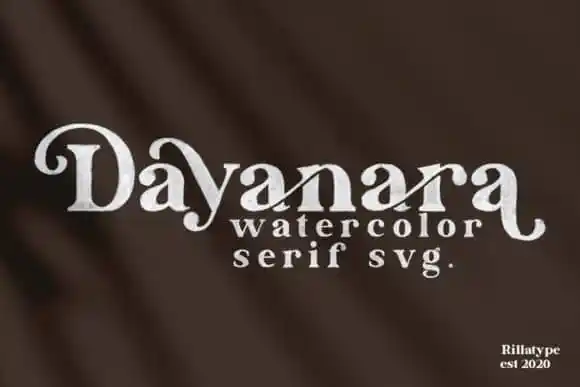
Dayanara Serif Font – Fonte Grátis
Dayanara Serif Font – Download Grátis
Dayanara Serif Font
A ‘Dayanara Serif Font’ é uma elegante tipografia serifada com estilos vintage moderno, que incorpora sutis ligaturas perfeitas para dar vida a textos mais complexos e detalhados. Este tipo de letra traz uma mistura única de sofisticação e simplicidade, o que a torna versátil tanto em propostas menores quanto grandes formatos. Suavemente elegante, Dayanara se destaca como um recurso gráfico indispensável para designers, seja no desenvolvimento de um site profissional ou na criação de um layout editorial. Seu design minimalista e moderno a torna uma escolha inegável para quem procura não apenas estilizar sua tipografia, mas também capturar o olhar do público final em cada projeto. Assim, Dayanara Serifa é uma fonte que se mantém atual, versátil e lhe permite expressar-se de maneira excepcional em qualquer ocasião.